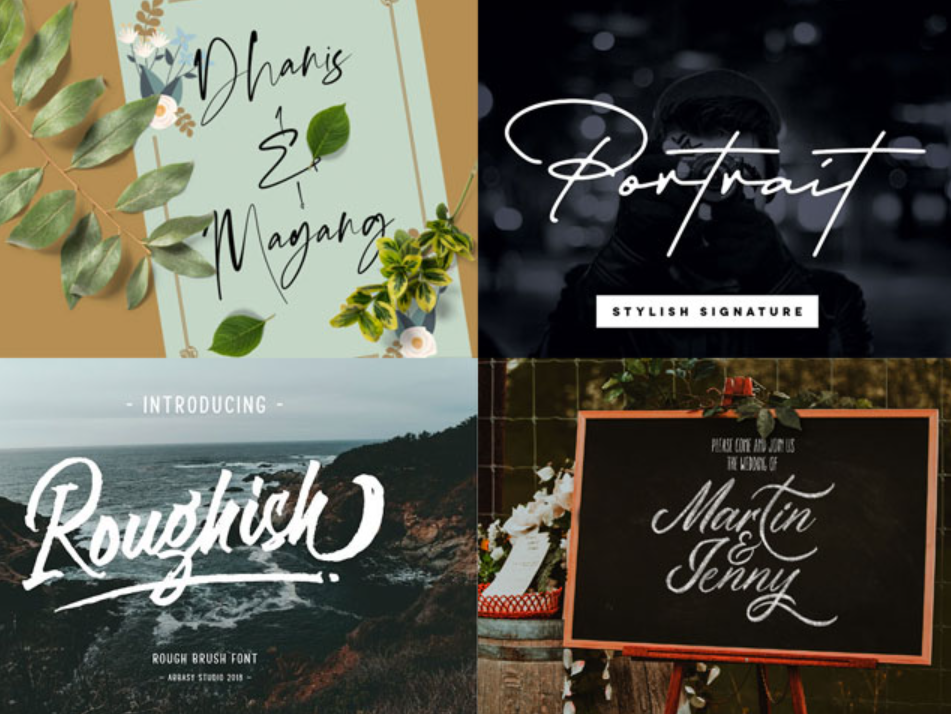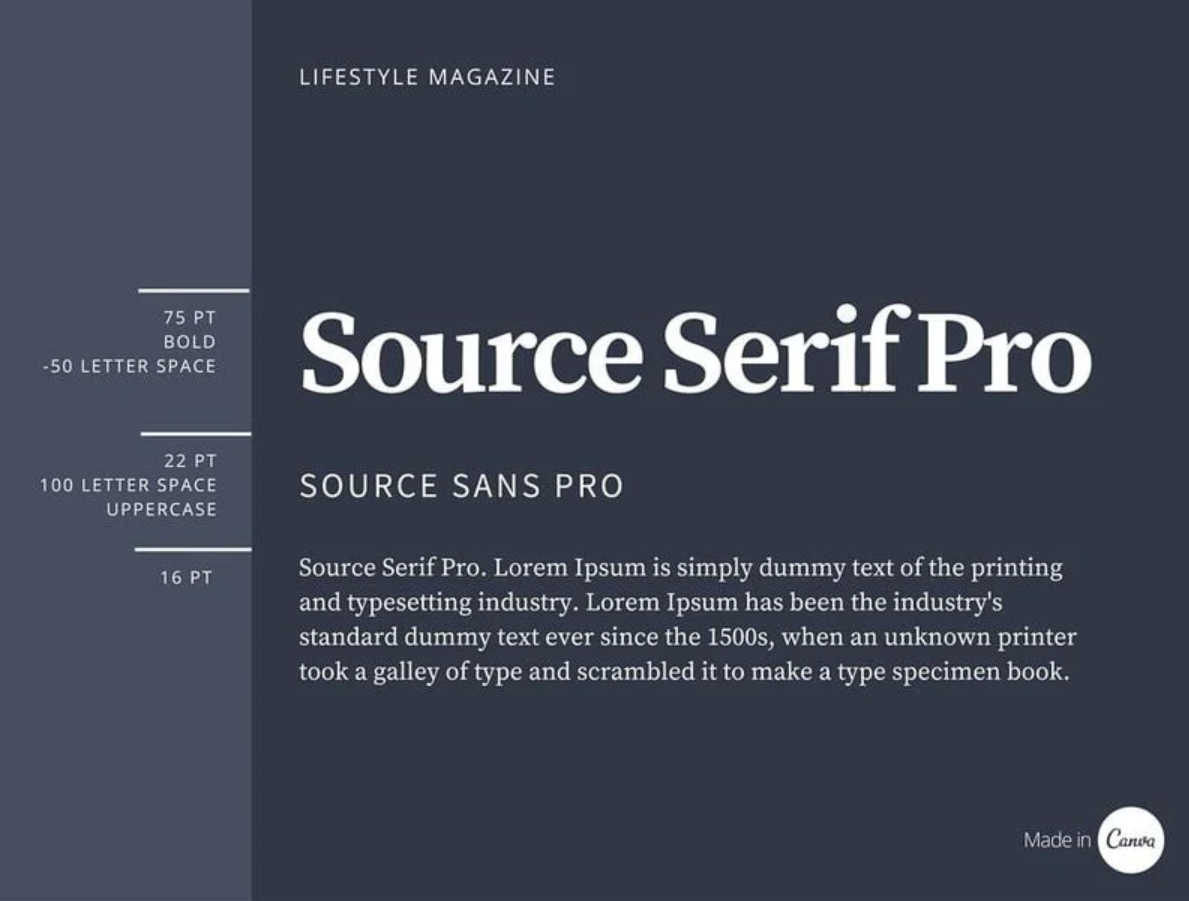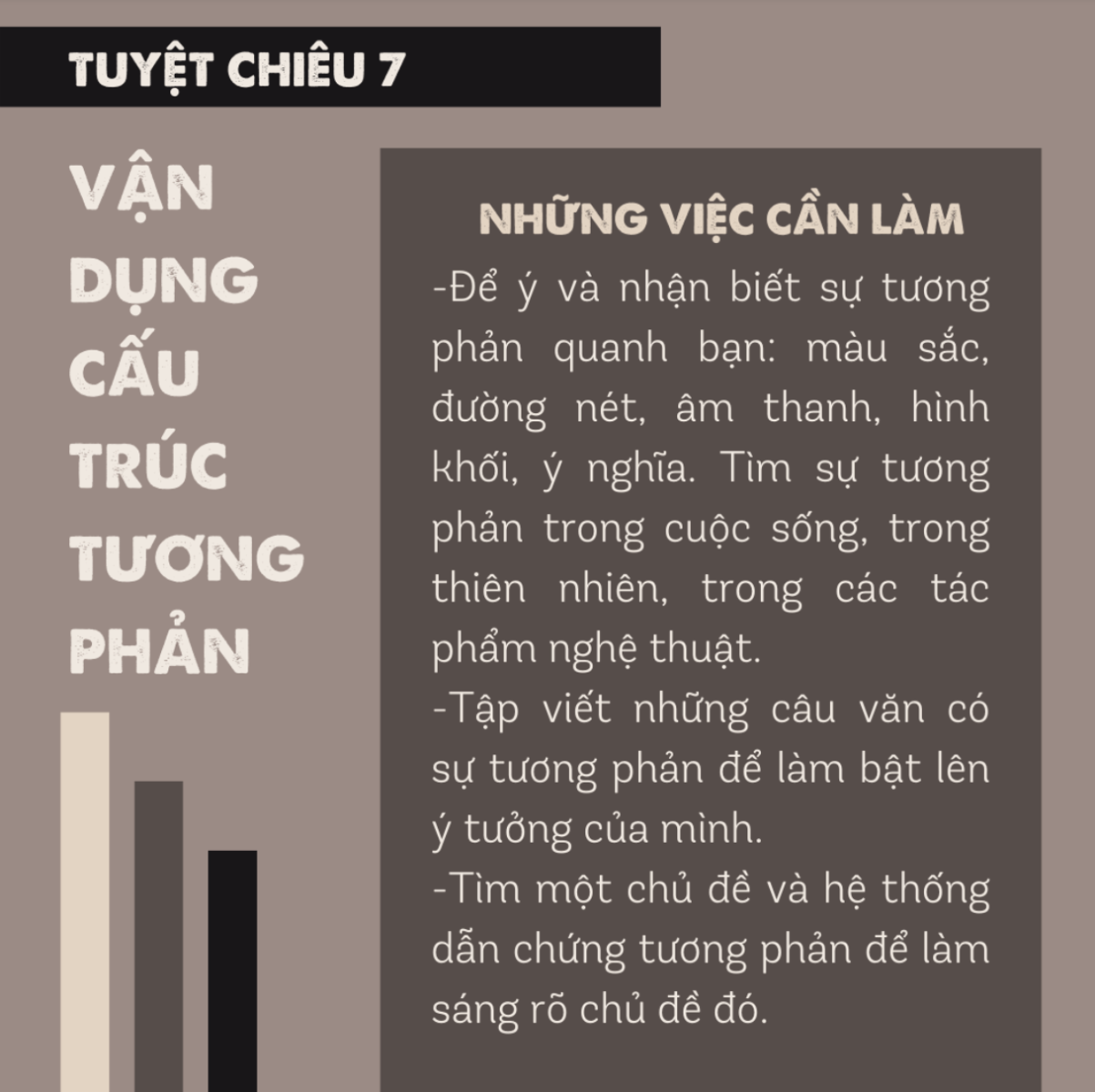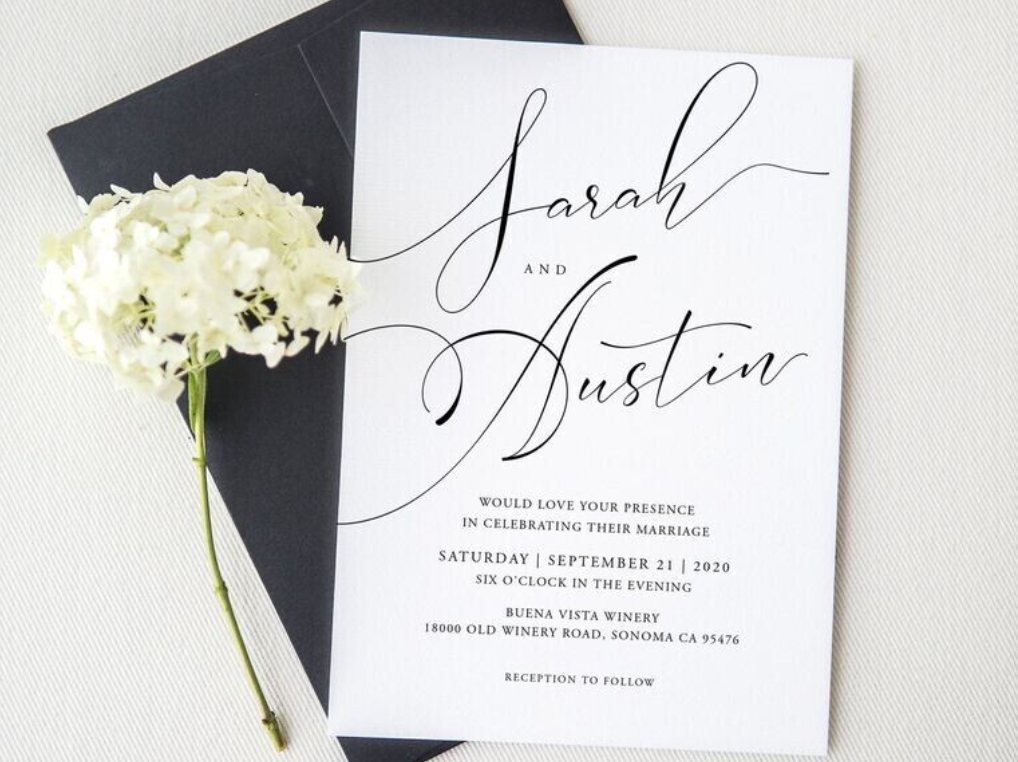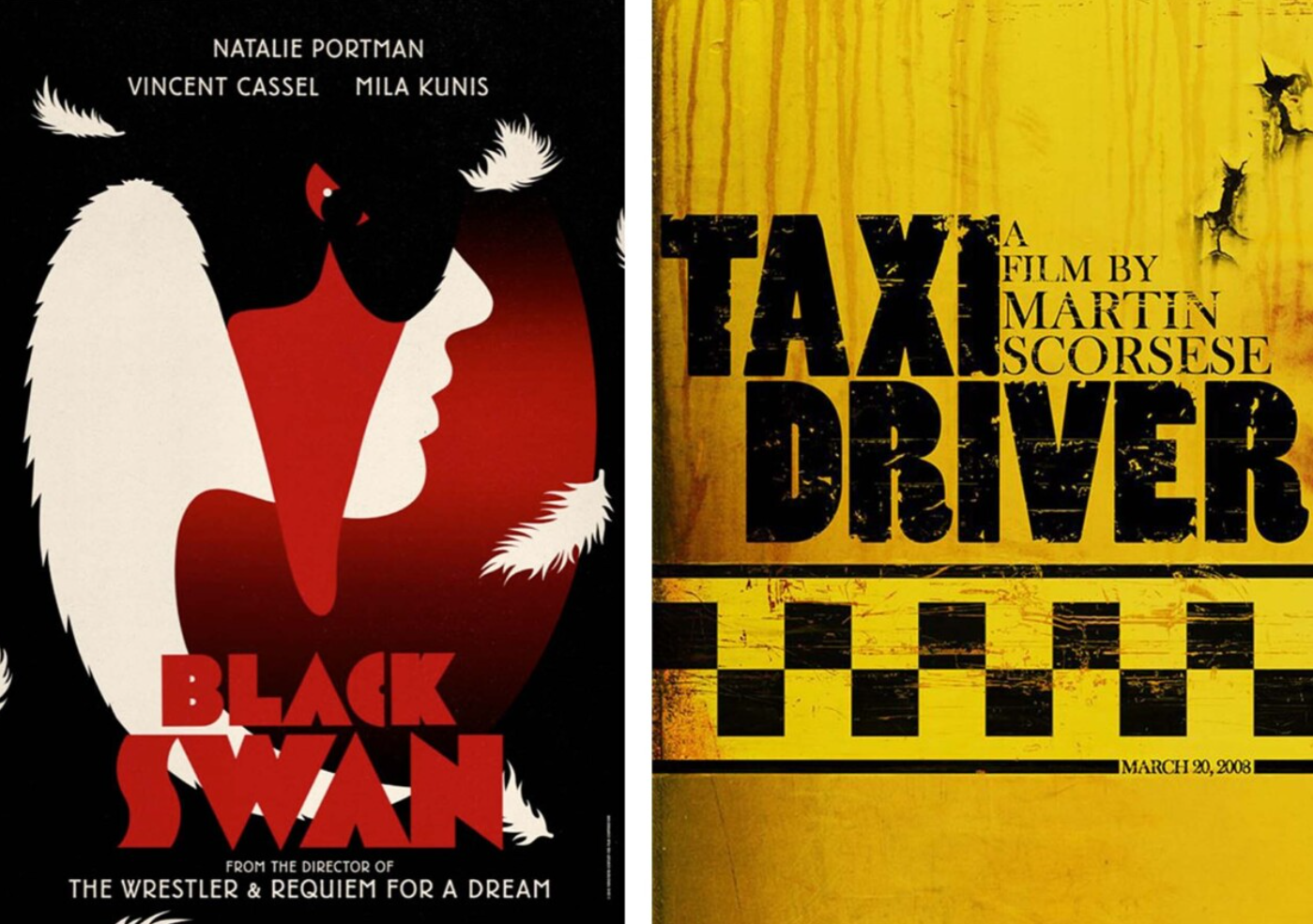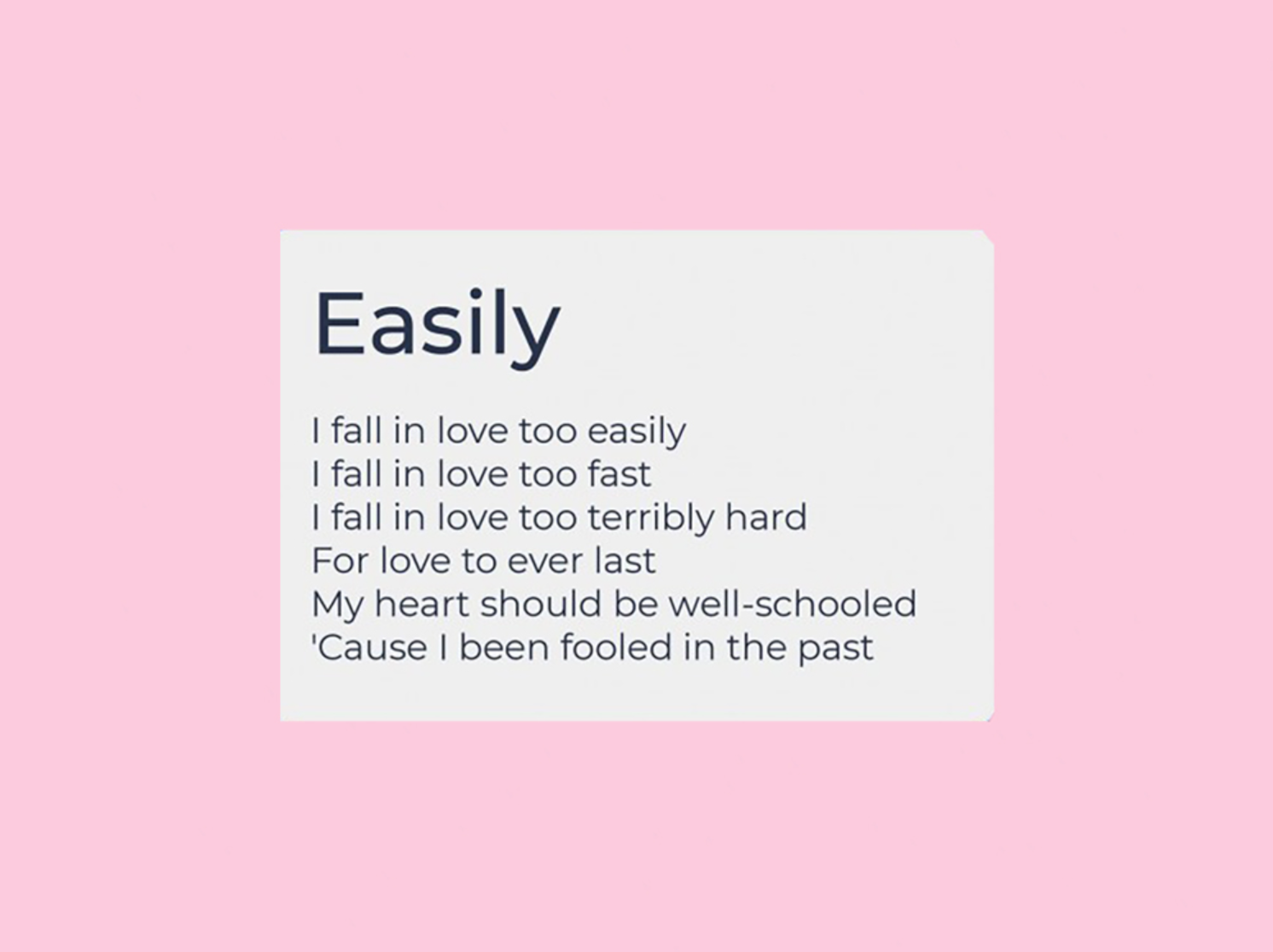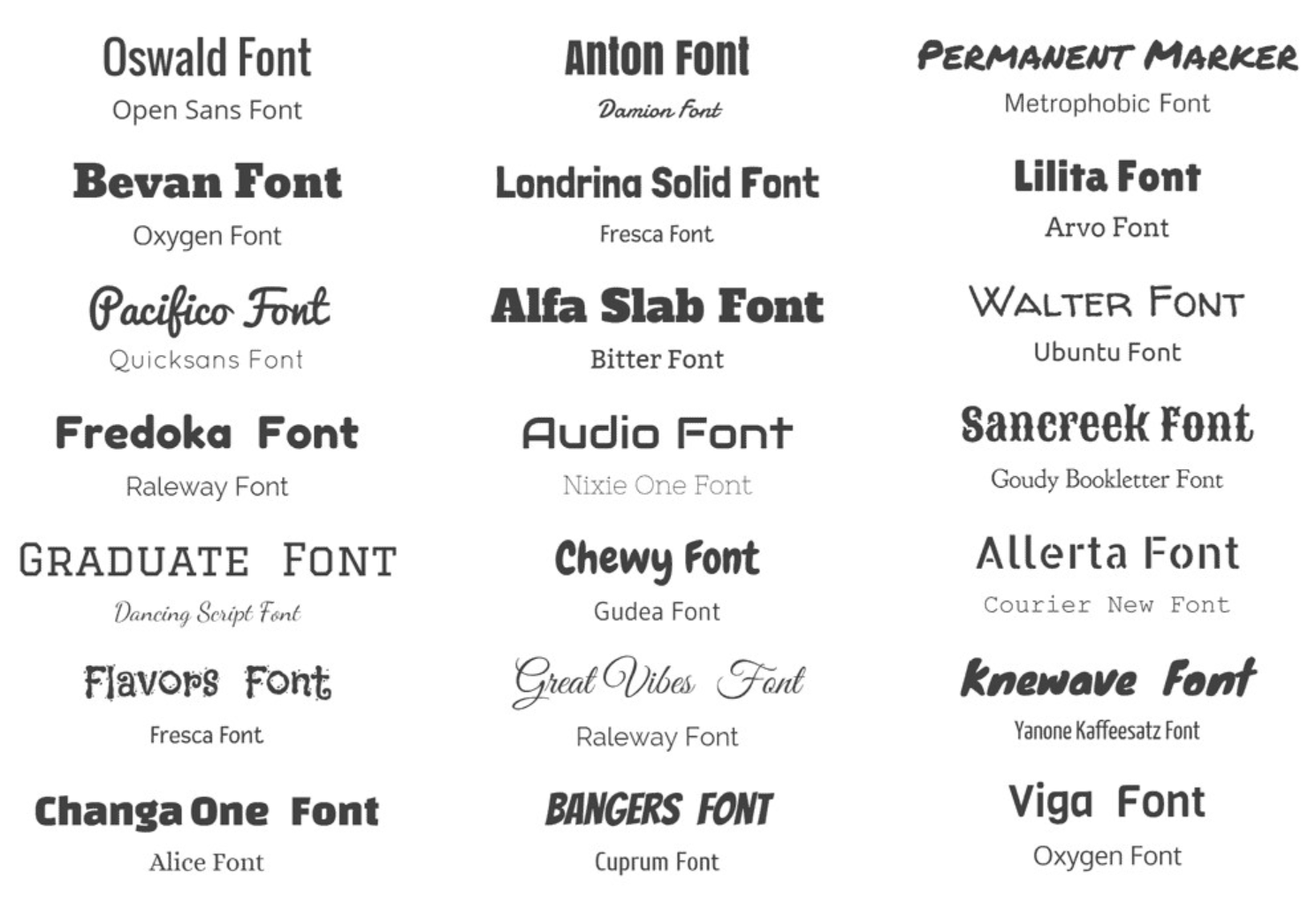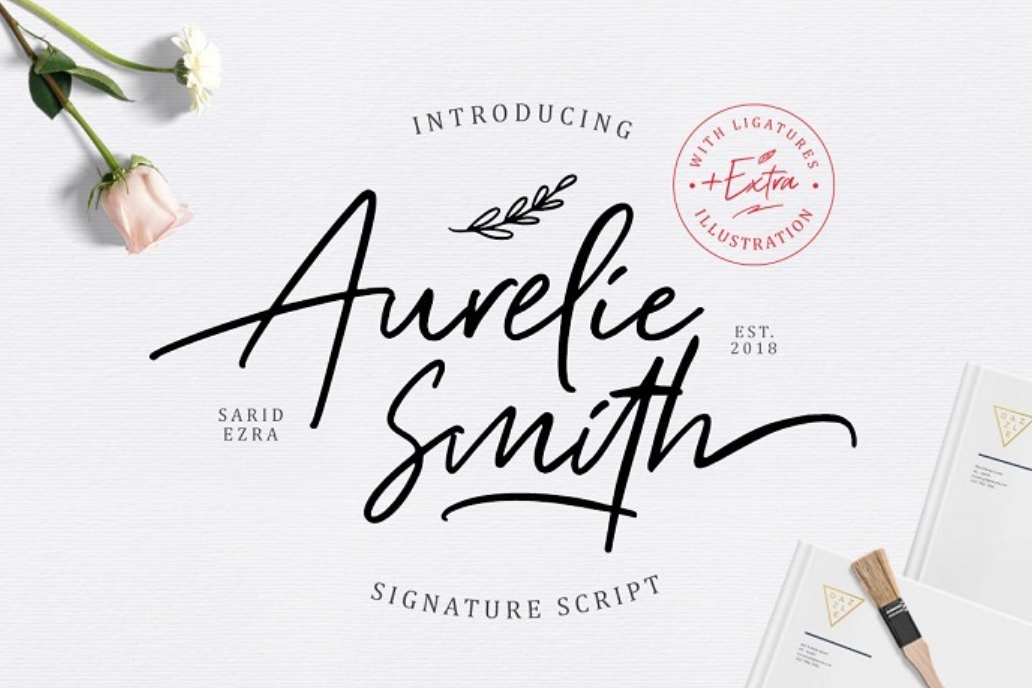
Nghệ Thuật Kết Hợp Font Chữ Để Tạo Dấu Ấn Riêng
Bạn sẽ được khám phá những bí quyết tinh tế để lựa chọn và phối hợp font chữ, giúp tạo nên phong cách thiết kế độc đáo và mang đậm dấu ấn cá nhân. Đây chính là cẩm nang dành cho những nhà thiết kế mong muốn bứt phá giới hạn truyền thống, tạo ra những tác phẩm ấn tượng và ghi dấu ấn sâu sắc trong lòng khách hàng.
Trong thế giới thiết kế ngày nay, mỗi chi tiết nhỏ đều có thể tạo nên sự khác biệt lớn. Một trong những yếu tố quan trọng nhưng thường bị xem nhẹ chính là font chữ. Những đường nét tinh tế, cách sắp xếp chữ và sự hài hòa giữa các kiểu chữ không chỉ góp phần làm đẹp cho thiết kế mà còn truyền tải thông điệp của thương hiệu một cách rõ ràng và sâu sắc.
Những năm tháng trải qua trong nghề thiết kế đã dạy tôi rằng, sự thành công của một dự án không chỉ đến từ ý tưởng hay màu sắc mà còn từ cách lựa chọn và kết hợp font chữ. Vì vậy, hôm nay, SaDesign xin gửi tới bạn những mẹo kết hợp font chữ hiệu quả, giúp bạn có thể tự tin tạo nên những thiết kế không chỉ đẹp mắt mà còn mang tính chuyên nghiệp cao. Trong bài viết này, chúng ta sẽ cùng nhau khám phá vai trò của font chữ trong thiết kế, cũng như những mẹo thực tiễn giúp bạn ứng dụng vào các dự án thiết kế thực tế. Hãy cùng khám phá nhé!
1. Vai Trò Của Font Chữ Trong Thiết Kế
1.1. Truyền Tải Thông Điệp
Font chữ không chỉ là các ký tự in trên giấy hay màn hình mà còn là công cụ truyền tải thông điệp, phản ánh phong cách và giá trị của thương hiệu. Một font chữ được chọn lựa kỹ càng sẽ:
Mỗi thương hiệu đều có một “ngôn ngữ” riêng. Chẳng hạn, một công ty công nghệ hiện đại có thể lựa chọn các font sans-serif với đường nét rõ ràng, trong khi một thương hiệu thời trang sang trọng có thể chọn font chữ có những đường cong mềm mại, tinh tế.
Font chữ mang lại cảm giác, từ sự trẻ trung năng động cho đến sự trầm lặng, cổ điển. Chính sự lựa chọn này có thể giúp người xem cảm nhận được thông điệp mà thiết kế muốn truyền đạt.
1.2. Tính Thẩm Mỹ Và Khả Năng Đọc
Không thể phủ nhận rằng, font chữ góp phần tạo nên vẻ đẹp tổng thể của một thiết kế. Một thiết kế chỉ thực sự hoàn hảo khi các yếu tố trực quan được cân đối, hài hòa:
Font chữ không chỉ giúp tách biệt các nội dung mà còn tạo ra một không gian thiết kế sạch sẽ, dễ nhìn. Sự kết hợp hài hòa giữa các kiểu chữ sẽ giúp nội dung trở nên sinh động, không bị “nặng nề” hay rối mắt.
Một thiết kế đẹp phải đảm bảo thông tin được truyền đạt một cách rõ ràng. Do đó, khả năng đọc của font chữ đóng vai trò rất quan trọng. Một font chữ dù đẹp đến đâu nếu khó đọc thì cũng không thực sự hiệu quả.
1.3. Phân Loại Font Chữ Và Ưu Nhược Điểm
Để có thể kết hợp font chữ hiệu quả, trước hết bạn cần hiểu rõ các loại font chữ chính:
Serif: Với những nét “chấm” ở cuối chữ cái, serif thường mang lại cảm giác truyền thống, sang trọng và dễ đọc trong các văn bản dài. Tuy nhiên, đối với thiết kế hiện đại, đôi khi serif có thể không phù hợp với phong cách trẻ trung.
Sans-serif: Đơn giản, sạch sẽ và hiện đại, sans-serif là lựa chọn lý tưởng cho các thiết kế hiện đại, công nghệ. Sự đơn giản của nó giúp tạo ra sự dễ đọc và tinh tế.
Script: Mang tính nghệ thuật, script mang lại sự tinh tế và cá tính riêng. Tuy nhiên, chúng thường khó đọc nếu sử dụng quá nhiều hoặc không đúng ngữ cảnh.
Display: Thường được sử dụng cho tiêu đề hoặc các điểm nhấn, display có kiểu dáng độc đáo và nổi bật. Tuy nhiên, cần cân nhắc kỹ lưỡng để không làm rối mắt người xem.
Hiểu được ưu nhược điểm của từng loại font sẽ giúp bạn dễ dàng hơn trong việc lựa chọn và phối hợp sao cho phù hợp với mục đích thiết kế.
2. Những cách kết hợp font chữ hiệu quả nhất
Thay vì dành ra hàng giờ hay hàng ngày chỉ để kết hợp tất cả các font chữ sẵn có, bạn có muốn biết một cách thông minh hơn để chọn ra các combo font chữ hoàn hảo không? Hãy cùng SaSesign tìm hiểu ngay các mẹo kết hợp font hiệu quả nhất dành cho thiết kế của bạn nhé!
2.1. Kết hợp font chữ không chân và font chữ có chân
Phép kết hợp font chữ đầu tiên, cũng là phép kết hợp kinh điển bậc nhất, chính là bộ đôi chữ không chân và chữ có chân. Hai font chữ này thường phối hợp cực kì ăn ý với nhau, đặc biệt là khi có sự tương phản trong kích cỡ các font chữ. Do đó, nếu như bạn đang vội và cần phải chọn nhanh 2 font chữ cho thiết kế của mình? Hãy kết hợp 1 font chữ không chân và 1 font chữ có chân nhé.
Để nói kỹ hơn về cách sử dụng cặp font chữ không chân và có chân, chúng ta sẽ bàn luận về câu hỏi "Chữ có chân hay chữ không chân dễ đọc hơn?". Thông thường, đối với các văn bản dài, font chữ có chân được ưu ái hơn vì nó giúp chúng ta tăng tốc độ đọc. Bạn có thể thấy rõ sự ưu ái này khi đọc các văn bản in ấn như sách báo, tạp chí,... Ngược lại, đối với văn bản hiển thị trên các website, ứng dụng điện tử,... thì font chữ không chân giành được lợi thế bởi sự tối giản trong các ký tự sẽ giúp chất lượng hiển thị tốt hơn trên các loại màn hình khác nhau.
2.2. Tạo sự tương phản giữa các phần văn bản
Nếu bạn hỏi rằng "Tại sao font chữ có chân và font chữ không chân lại hợp nhau đến thế?" thì mình sẽ trả lời lý do là bởi chúng tạo ra sự tương phản về mặt thị giác. Trên thực tế, bạn có thể tạo ra sự tương phản cho các phần văn bản trong thiết kế bằng rất nhiều cách, ví dụ như chọn typeface, điều chỉnh kích cỡ, độ dày/mỏng,...
Trong hình vẽ phía trên, bạn có thể thấy một sự kết hợp hài hòa giữa một font chữ nét đậm, mang lại cảm giác vững chãi và một font chữ cao, thanh mảnh. Tưởng như quá khác biệt, nhưng chính sự đối lập hoàn toàn của 2 font chữ này lại đem đến cho tổng thể thiết kế sự cân bằng hoàn hảo.
2.3. Kết hợp các font chữ bổ túc
Font chữ giống con người ở điểm nào? Chính là đều sở hữu các tính cách đặc trưng như trang trọng, phổ thông, tinh nghịch, sang trọng,... Khi thiết kế bất kỳ ấn phẩm nào, bạn cũng sẽ cần đảm bảo các font chữ được lựa chọn phù hợp với thông điệp của ấn phẩm. Ví dụ như một font chữ script hoặc calligraphy sẽ là sự lựa chọn hoàn hảo cho một tấm thiệp mời đám cưới, nhưng chắc chắn không phù hợp với các tờ báo kinh tế.
"Trái dấu thì hút nhau." Định luật này không chỉ đúng với các ứng dụng vật lý hay các tình huống trong cuộc sống, mà còn đúng với cả các font chữ. Bạn sẽ thấy rằng các font chữ với 2 thái cực trái ngược sẽ tạo nên một bộ đôi hoàn hảo khi đứng cạnh nhau. Các font chữ này được gọi là các font chữ bổ túc.
Vậy bạn sẽ áp dụng các font chữ bổ túc như thế nào? Nếu bạn đã chọn sẵn một font chữ sỡ hữu tính chất mạnh mẽ (ví dụ như font chữ trong hình dưới đây), hãy kết hợp nó với một font chữ trung tính và nhỏ gọn hơn. Cặp font này sẽ giúp thiết kế của bạn trở nên cân bằng, hài hòa.
Có thể thoạt đầu bạn sẽ thấy cách kết hợp các cặp font chữ bổ túc không khác gì một trò chơi đoán từ, vì kết quả lựa chọn các font chữ hoàn toàn dựa trên cảm tính của bản thân. Tuy nhiên, điều đó không phải một vấn đề gì to tát. Chỉ cần bạn để ý tới cách các font chữ bắt cặp với nhau trên các website thông thường, các biển hiệu ngoài đường hay bao bì các sản phẩm sử dụng hàng ngày, bạn sẽ dần dần hình thành cho mình tư duy kết hợp font chữ.
2.4. Kết hợp các font chữ cùng một họ
Sử dụng các font chữ cùng họ luôn là sự lựa chọn an toàn nhất dành cho thiết kế của bạn, bởi các font chữ này được tạo ra để phối hợp với nhau. Với phép kết hợp này, bạn hãy sử dụng các họ sở hữu nhiều lựa chọn cho font chữ (bao gồm các thuộc tính weight, style, case) để đảm bảo rằng bạn sẽ có đủ các font chữ cần dùng. Ngoài ra, bạn sẽ cần tạo ra độ tương phản giữa các phần văn bản sử dụng các font chữ khác nhau.
Điểm mạnh của việc giới hạn các font chữ trong cùng một họ chính là bạn có thể tập trung vào sự đồng nhất trong thiết kế của mình. Việc chọn các cặp font chữ phù hợp luôn tốn rất nhiều thời gian. Thay vào đó, nếu bạn đã có một họ font chữ nhất định, bạn vừa có thể rút ngắn thời gian cho bước chọn font, vừa có thể tạo ra một thiết kế hoàn chỉnh hơn.
2.5. Giới hạn số font chữ sử dụng trong thiết kế
Nếu như bạn không muốn gò bó bản thân trong sự an toàn của việc kết hợp các font chữ cùng một họ, thì bạn hoàn toàn có thể mở rộng các lựa chọn của mình. Tuy nhiên, chắc chắn rằng bạn cần phải đặt giới hạn cho số lượng các font chữ sẽ sử dụng.
Có thể bạn đã nghe nhiều lời khuyên về việc chọn font chữ cho thiết kế, rằng chỉ nên sử dụng 2 đến 3 font chữ mà thôi. Đó là một quy luật phổ biến đã được ứng dụng vào rất nhiều các ấn phẩm trên thực tế.
2.6. Tránh sử dụng các font chữ quá giống nhau
Vấn đề của các font chữ có quá nhiều điểm tương đồng chính là việc chúng không thể tạo ra sự tương phản cần thiết để phân cấp các phần văn bản trong thiết kế. Khi sử dụng các font chữ này, bất kỳ điểm khác nhau nào cũng sẽ giống một lỗi typo hơn là một font chữ được chọn có chủ đích.
Có một cách đơn giản để kiểm tra liệu 2 font chữ có giống nhau nhiều hơn cần thiết không: Đặt 2 font chữ cạnh nhau trên màn hình, ngồi lùi về đằng sau và nheo mắt. Nếu bạn thấy không có gì khác nhau giữa 2 dòng chữ, đó là dấu hiệu của một phép kết hợp font chữ thất bại. Lúc này, bạn sẽ cần tăng sự tương phản trong các phần văn bản của mình.